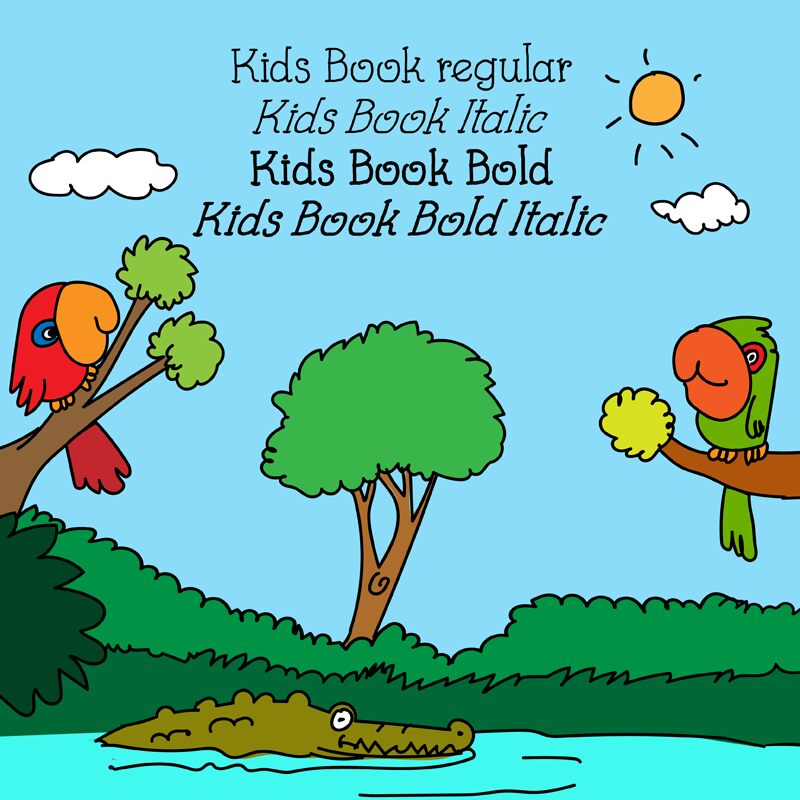
Kids Book Bold od Galdino Otten Fonts je bezplatné ručně psané písmo s uvolněným, příběhovým rytmem. Zaoblené zakončení tahů působí měkce a přívětivě, aniž by však sklouzlo k přílišné „cukrkandlovosti“. Nerovnoměrné kolísání a vysoké, lehce roztřesené tvary mu dodávají vzhled ručně psaných názvů kapitol, což je mnohem živější než upjatá školní písma.
Skvěle funguje na obálkách dětských knih, pracovních listech, třídních plakátech, pozvánkách na narozeniny nebo obalech hraček, kde tento poskakující rytmus dělá krátké texty přátelštějšími a neformálnějšími. Písmo dodává štítkům i nadpisům aktivit osobitý, „ruční“ nádech, který se pro značky zaměřené na děti hodí mnohem lépe než neutrální standardní rukopis.